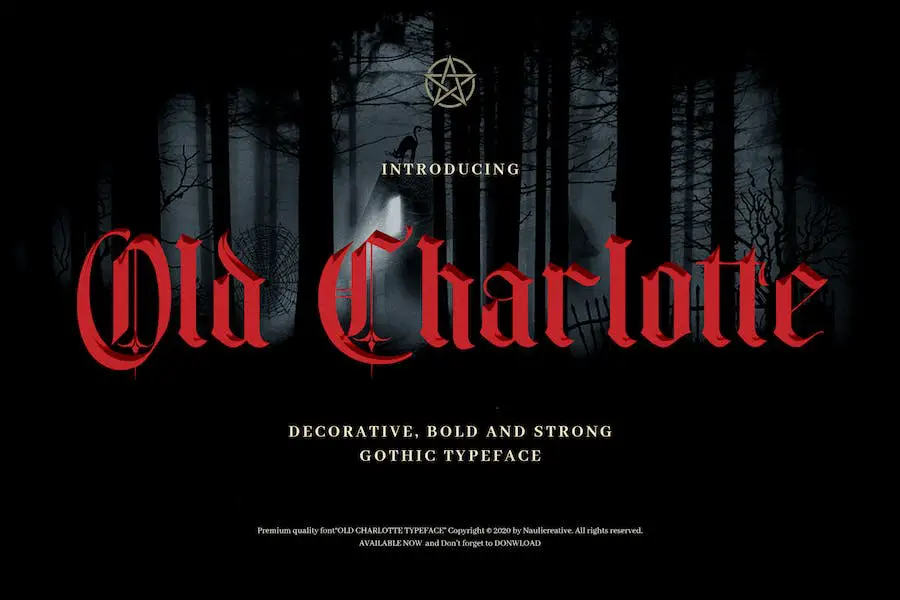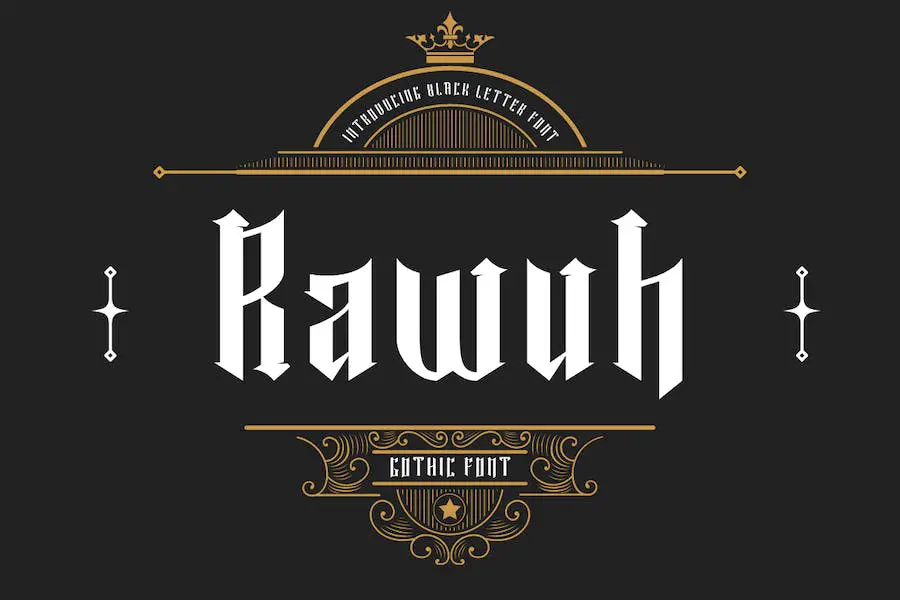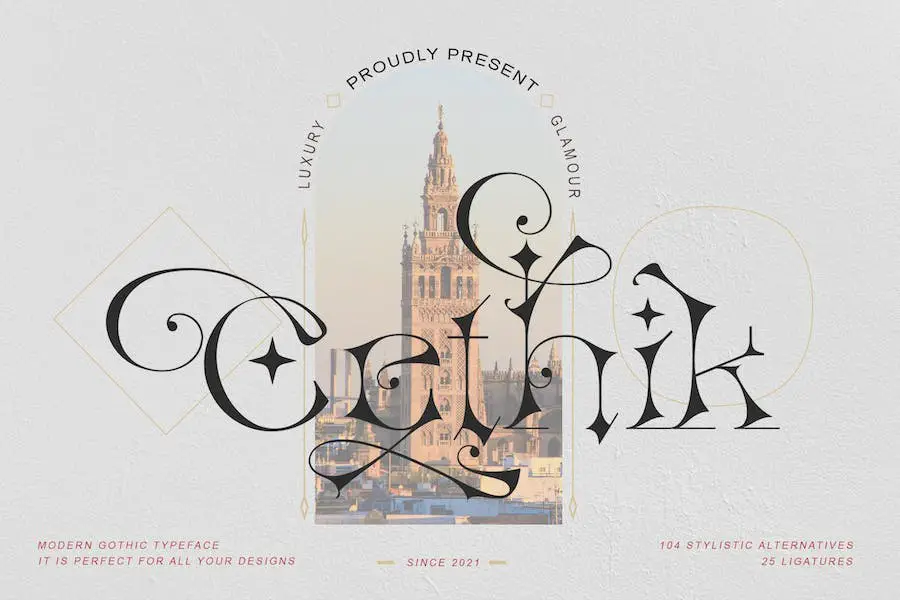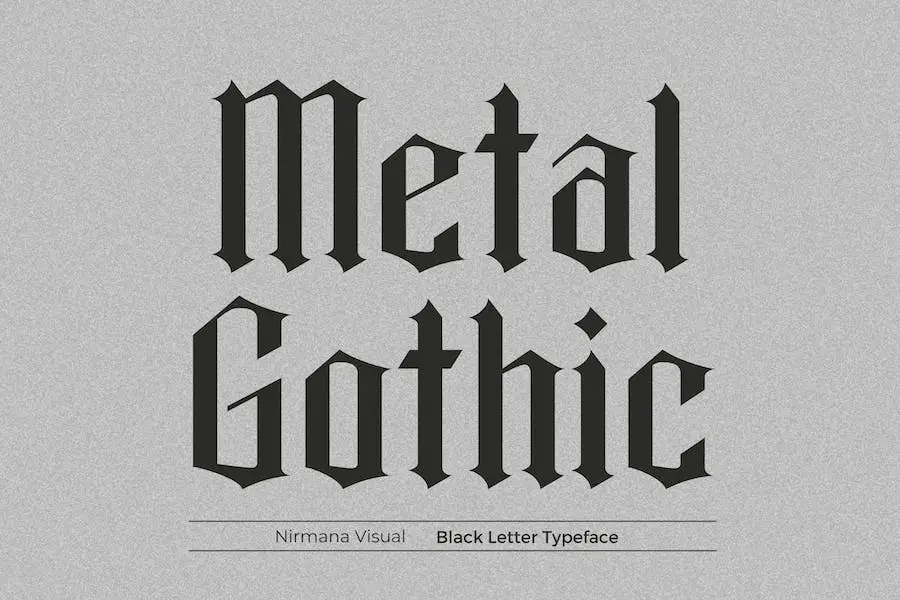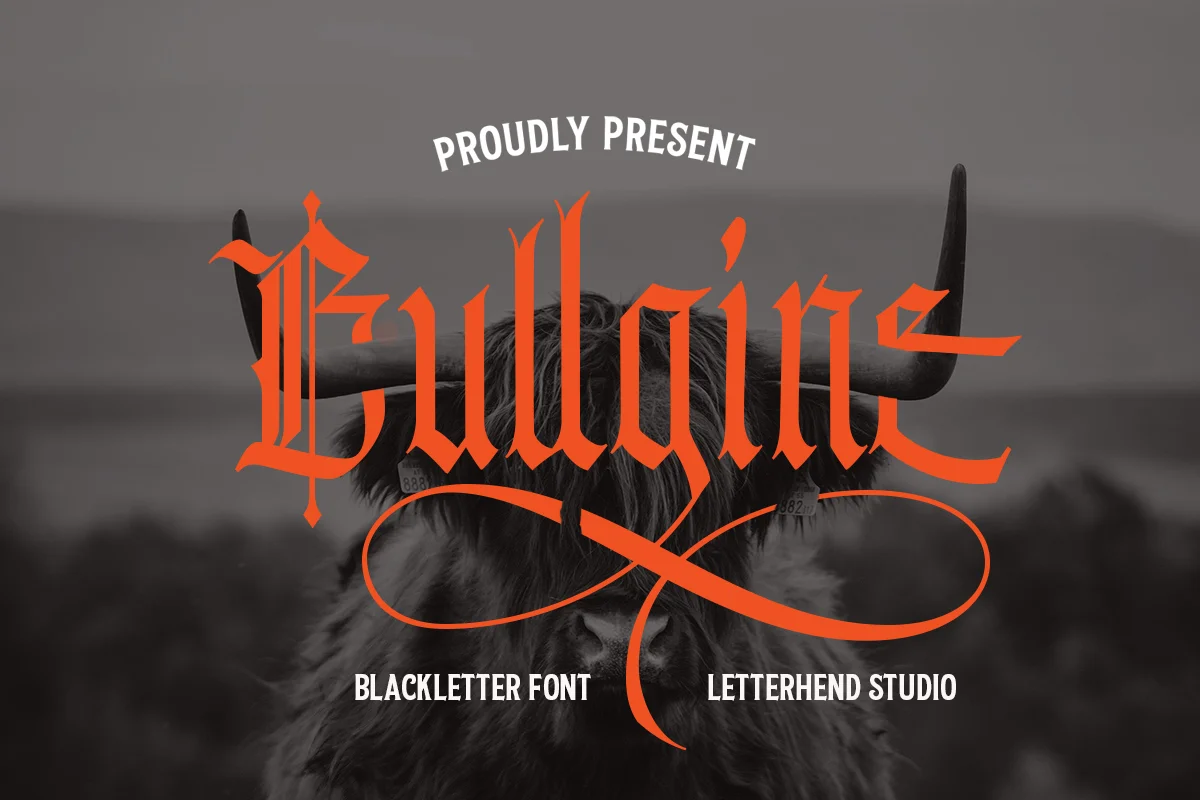
cambridge
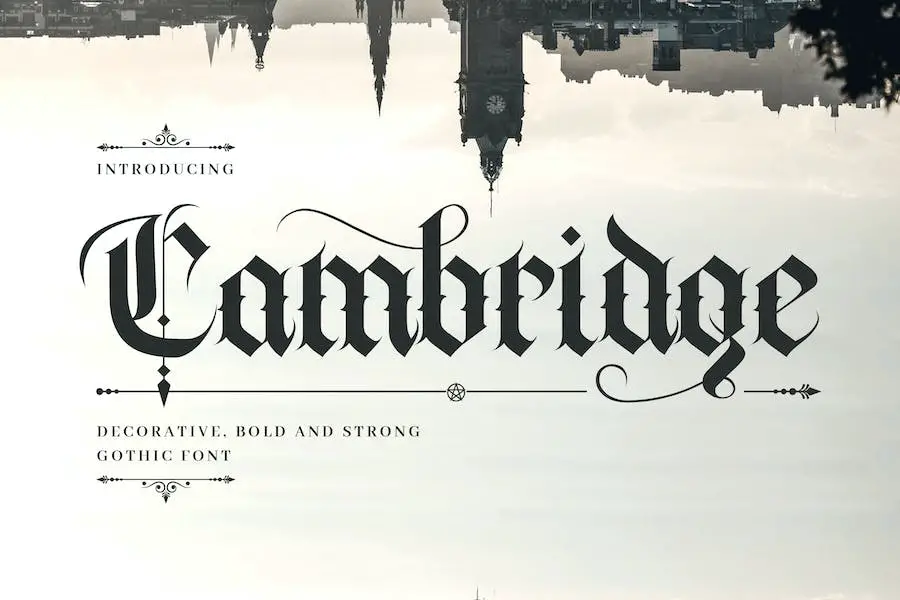
Cambridge es una fuente decorativa de letras a mano en negrita que emana un ambiente gótico medieval. Si está buscando una fuente que mejore sus diseños y los haga destacar, Cambridge es la elección perfecta.
Para los diseñadores gráficos que buscan agregar un toque de estilo gótico a sus proyectos, Cambridge es una excelente opción. Con su estilo de letras único y su llamativo diseño, seguramente llamará la atención y hará una declaración. Cuando busque Adobe Gothic Fonts, ¡no pase por alto Cambridge!
Killuminati
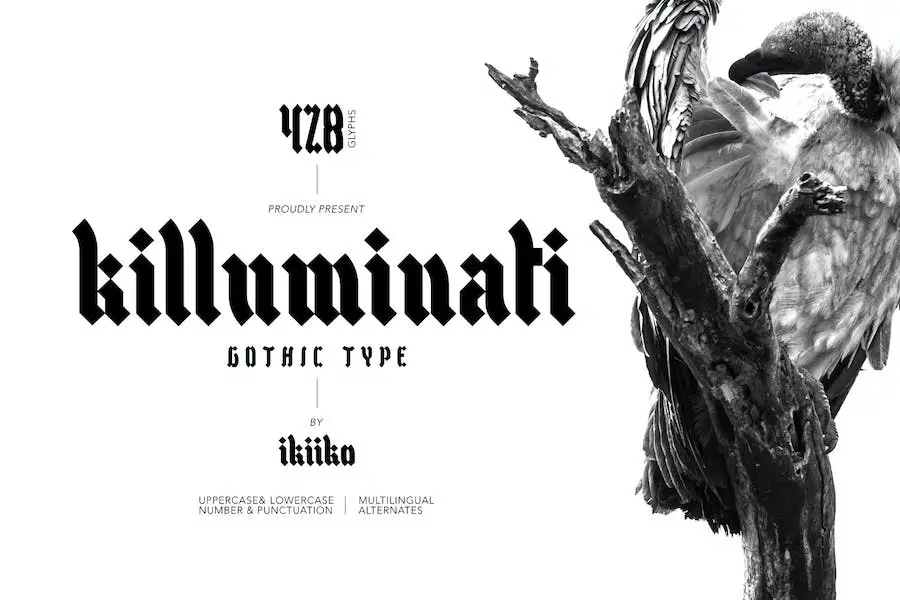
Killuminati es una tipografía gótica diseñada por ikiiko que combina el estilo inglés antiguo con un diseño de letra gótica moderna. Sus esquinas afiladas y curvas le dan un atrevimiento único que es perfecto para varios diseños, como carteles de eventos, logotipos, diseños de revistas, artículos de moda y citas.
Esta fuente viene con letras mayúsculas y minúsculas, números y puntuación, alternativas y soporte multilingüe. Los archivos de formato TTF y OTF lo hacen compatible tanto con PC como con Mac.
Killuminati es una excelente opción para aquellos que buscan elevar sus proyectos con un toque de estilo gótico.
fayté
Fayte es una fuente de letra negra moderna perfecta para aquellos que buscan agregar un toque de estilo vintage a sus proyectos de diseño. Es un tipo de letra versátil que se puede usar en una variedad de aplicaciones, desde marcas hasta publicaciones de Instagram, carteles impresos, revistas, moda y más.
Si está buscando fuentes góticas para el diseño de circuitos u otros proyectos, Fayte podría ser justo lo que necesita. Su versión contemporánea del diseño clásico de letras negras lo hace accesible y adaptable, al mismo tiempo que conserva su estilo inconfundible.
tierra
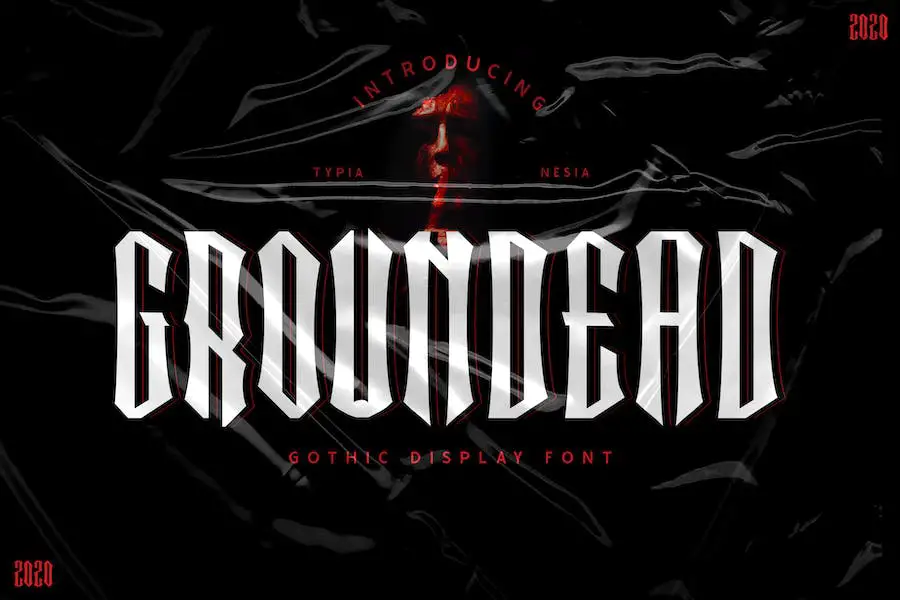
Groundead Horror Font es un tipo de letra versátil que se puede utilizar para diversas necesidades de diseño, como logotipos, marcas, publicidad y más. Es una excelente opción para aquellos que buscan una fuente que exuda una atmósfera gótica y un ambiente de terror.
Una de las características sobresalientes de Groundead es su estilo escrito a mano, que agrega una personalidad única a cualquier proyecto en el que se use. La fuente es perfecta para crear carteles, portadas de libros y diseños editoriales de aspecto antiguo. Además, se puede usar para diseños modernos, lo que la convierte en una excelente opción para aquellos que desean mezclar elementos antiguos y nuevos.
gótico
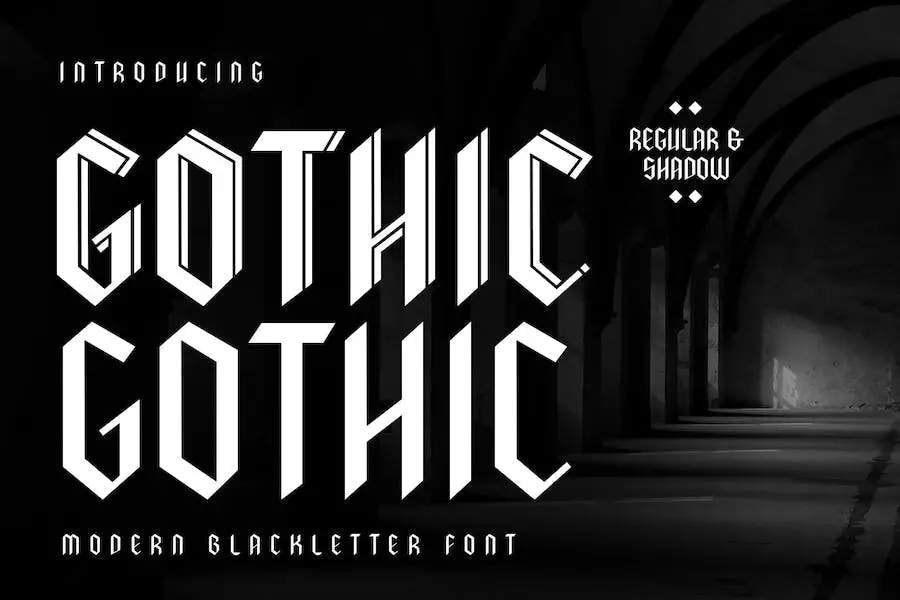
Fuentes góticas para uso comercial: prepárese para crear diseños impresionantes con gótica, una fuente gótica moderna que combina elementos góticos, romanos y de estilo antiguo. Con esta fuente, puede lograr fácilmente formas y variaciones únicas seleccionando alternativas en segundos.
Diseñado para uso comercial, Gothic es una opción ideal para los diseñadores que desean elevar sus proyectos con un toque de estilo gótico.
Su versatilidad y facilidad de uso lo convierten en un elemento imprescindible en su colección de fuentes. Entonces, si está buscando una fuente que le dé un toque único a sus diseños, definitivamente vale la pena echarle un vistazo a Gothic.
Samaz
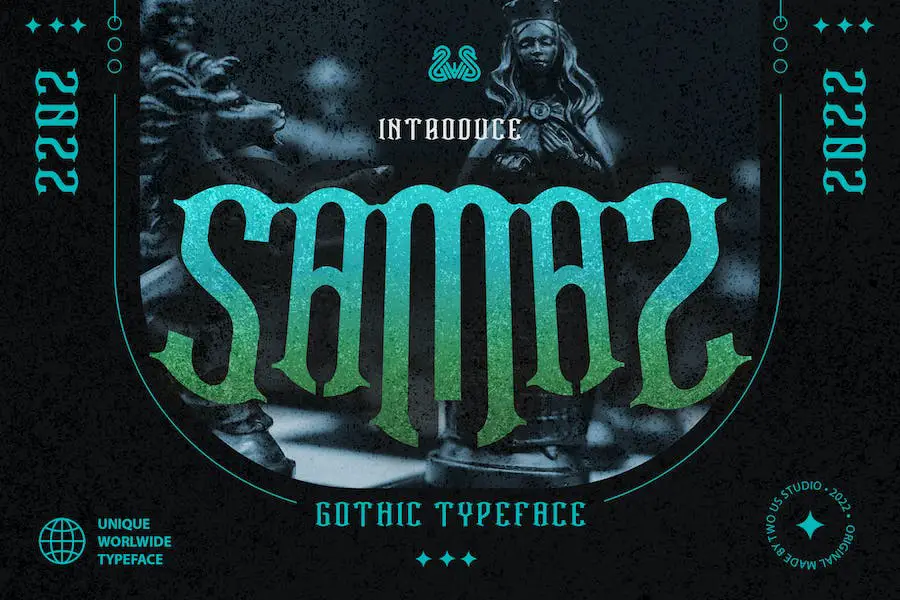
Samaz – Gothic Vintage Typeface es una fuente única que se puede utilizar para fines personales o comerciales.
Con su escritura gótica distintiva, agrega un toque vintage a cualquier diseño de proyecto. La fuente viene en tres formatos diferentes: OTF, TTF y WOFF, lo que facilita su uso con una amplia variedad de aplicaciones.